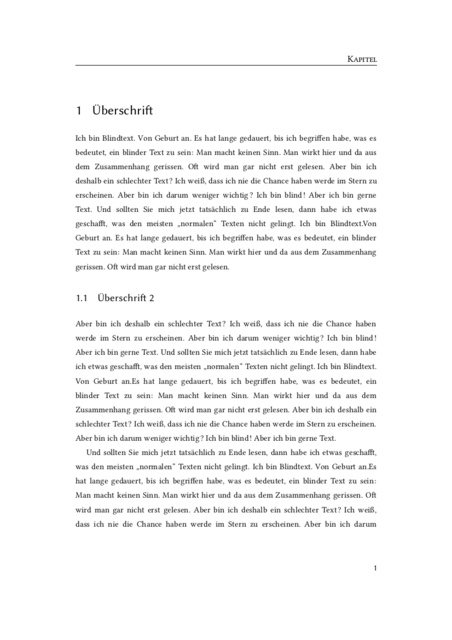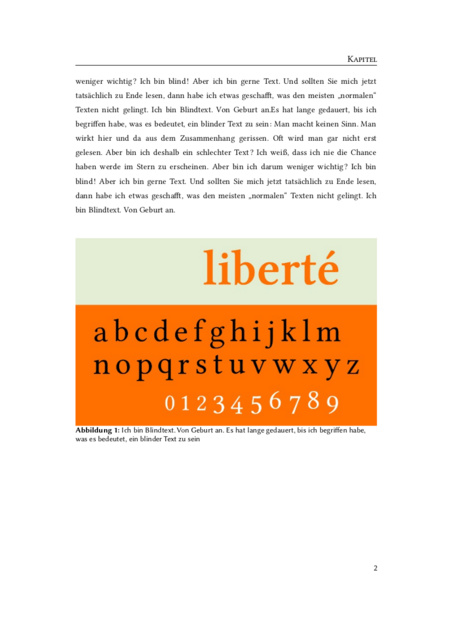
Meinungen und Anregungen zum Satzspiegel
ich bin gerade dabei meine Bachelorarbeit zu vollenden und mache mir nun schon seit ein paar Wochen Gedanken über die Typografie. Ich würde mich als Typografieinteressierten, aber bei weitem nicht als Kenner bezeichnen und habe deshalb bezüglich der Typografie einige Fragen.
Layout:
• Gedruckt wird einseitig auf DIN A4 mit Softcover/Leimbindung
• Außen-, Kopf- und Bundsteg: 35mm. Fußsteg: 459mm
Fließtext:
• Linux Libertine G in 11pt
• 1,5 Zeilenabstand
• Durchschnittlich 83 Zeichen pro Zeile
Überschriften:
• Linux Biolinum G in 17,5pt (Ebene 1)
• 14pt (Ebene 2)
• 12pt (Ebene 3)
Und zwei Bilder:
Nun zu meinen Fragen:
• Passen die Libertine und die Biolinum so zusammen?
• Sollte ich den Abstand zwischen Kopfzeile und Fließtext vergrößern?
• Ist die Biolinum in 10pt als Abbildungstext in Ordnung?
• Wie viel Platz sollte ich beim Bundsteg bei Leimbindung mit ca. 80 Seiten ungefähr wegrechnen damit der Text mittig bleibt?
• Irgendwelche sonstigen An- oder Bemerkungen?
Noch eine Anmerkung: Ich würde gerne bei der Libertine G bleiben, weil die Graphite Featrues für LibreOffice wirklich sehr cool sind und mir ne Menge Arbeit ersparen.
Edit: Ich seh gerade, dass die Bilder recht klein sind. Als Alternativen: http://i.imgur.com/o9Ven.png und http://i.imgur.com/R8tli.png
Als erstes stört mich diese Linie oben, wenn die keinen expliziten Zweck hat: weg damit. Unten kann man sowas eher mal machen, dann hat der Text ein Fundament auf dem er stehen kann; oben wirkt das (vor allem so eng) immer erdrückend.
Meine 2 ¢ nachdem ich allerdings nur die kleinen Bilder angesehen habe.
[*]Ist die Biolinum in 10pt als Abbildungstext in Ordnung?
Ich würde auf jeden Fall darauf achten, dass der Größenunterschied zum Fließtext deutlich ist. Das kann man (ich zumindest) am besten an einem 1/1-Ausdruck beurteilen. Außerdem sitzt die Bildunterschrift zu dicht am Bild (hast du ein Grundlinienraster?).
Grundlinienraster gibts bei LibreOffice imo nicht. Ich hab den unteren Rahmen der Kopfzeile entfernt und den Abstand vom Abbildungstext zum Bild erhöht. Siehe: http://i.imgur.com/QbxpS.png
Und hier die Libertine und Biolinum im Vergleich:
Das ist jetzt zwar nicht zum Satzspiegel, aber dennoch eine Anregung: Der Fließtext ist sehr schwer lesbar, weil die Wortabstände viel zu groß sind. Hast du absichtlich auf Trennungen verzichtet?
Mich stören die Kapitälchen in der Kopfzeile. Wenn schon Großbuchstaben, dann doch gleich Versalien. Der Zeilenabstand des Fließtextes ist für meinen Geschmack zu groß. (Ja, ich weiß, die Vorgabe will das so – aber die soll ja eigentlich nur die schlimmsten Textwüsten verhindern, ich habe noch nie erlebt, dass kleinere Abweichungen moniert worden sind, wenn’s insgesamt gut ausgesehen hat und leicht lesbar war).
@bertel: Ich hab die Silbentrennung im Beispiel vergessen, sollte eigentlich rein.
@Dieter Stockert: Besser so? 130% Zeilenabstand kommt mir irgendwie recht klein vor.
ich würde die Abstände nach einer Überschrift etwas kleiner wählen als den Abstand davor.
Besser so? 130% Zeilenabstand kommt mir irgendwie recht klein vor.
Besser. Allerdings würde ich den Zeilenabstand nicht in Prozentwerten einstellen (das bezieht sich ja auf die Schrift und da kann es passieren, dass bei einem Sonderzeichen aus einer anderen Schrift (oder auch nur bei hoch- oder tiefgestellten Zeichen) sich innerhalb eines Absatzes der Abstand zweier Zeilen verändert. Der Zeilenabstand sollte deshalb besser auf einen festen Wert eingestellt werden.
Text in Versalien bräuchte eine leichte Sperrung.
Bzw. Versalausgleich (siehe API bei Kapitel)
Also von den Versalien hab ich Abschied genommen, das sah bei langen Überschriften blöd aus. Der Zeilenabstand ist jetzt 55mm
Ich würde auf jeden Fall darauf achten, dass der Größenunterschied zum Fließtext deutlich ist. ... Außerdem sitzt die Bildunterschrift zu dicht am Bild (hast du ein Grundlinienraster?).
Umlauf des Bildes = 0?
In einem Fall, wo man die Bildunterschrift kaum noch kleiner kriegt, setze ich ihn zur besseren Unterscheidung vom Fließtext kursiv.
Umlauf des Bildes = 0?
In den meisten Fällen, ja. Nur zum Abbildungstext sind 20mm Abstand.
In einem Fall, wo man die Bildunterschrift kaum noch kleiner kriegt, setze ich ihn zur besseren Unterscheidung vom Fließtext kursiv.
Das ist aber nur ein Anfangswert, der dann nach Augenmaß angepaßt werden muß. (Je länger die Zeilen sind, desto größer muß der Zeilenabstand sein.)
Es gibt verschiedene Möglichkeiten, die Seite so aufzuteilen, daß die Zeilen eine günstigere Länge haben. Du kannst, wenn Du einspaltig setzt, eine breite Randspalte verwenden. In diese Randspalte kannst Du Marginalien setzen, sie bietet sich aber auch für handschriftliche Anmerkungen an. Eine andere Möglichkeit ist, zweispaltig zu setzen, wodurch Du mehr Text auf einer Seite unterbringen kannst.